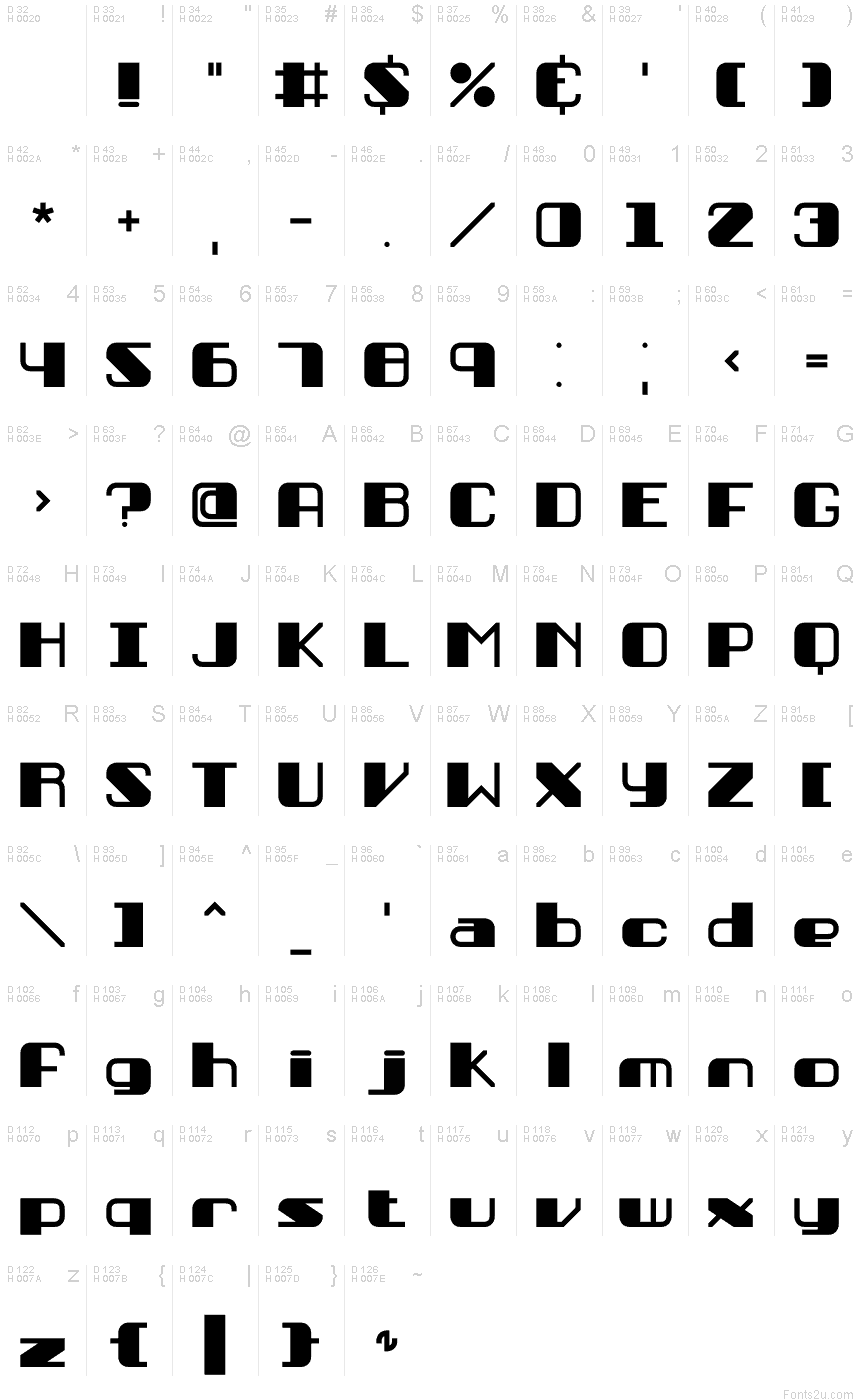
Persuasion od AEnigma Fonts to darmowy, retro-futurystyczny krój pisma typu display, utrzymany w eleganckim klimacie lat 70. Litery łączą w sobie szerokie, zaokrąglone kształty z gwałtownymi cięciami i ostrymi połączeniami, co nadaje całości płynny, nieco przysadzisty rytm – z nutą „space-age” i swobodą w stylu lounge.
Świetnie sprawdzi się na okładkach płyt, w nagłówkach plakatów, na okładkach magazynów, w brandingu klubowym oraz wszędzie tam, gdzie krótka fraza ma przyciągać wzrok. Jako darmowy font, sprawdzi się również w logotypach czy monogramach; rzeźbione krzywizny i ostre kliny sprawiają, że nawet kilka znaków zyskuje wyrazistą, graficzną sylwetkę.
Persuasion BRK